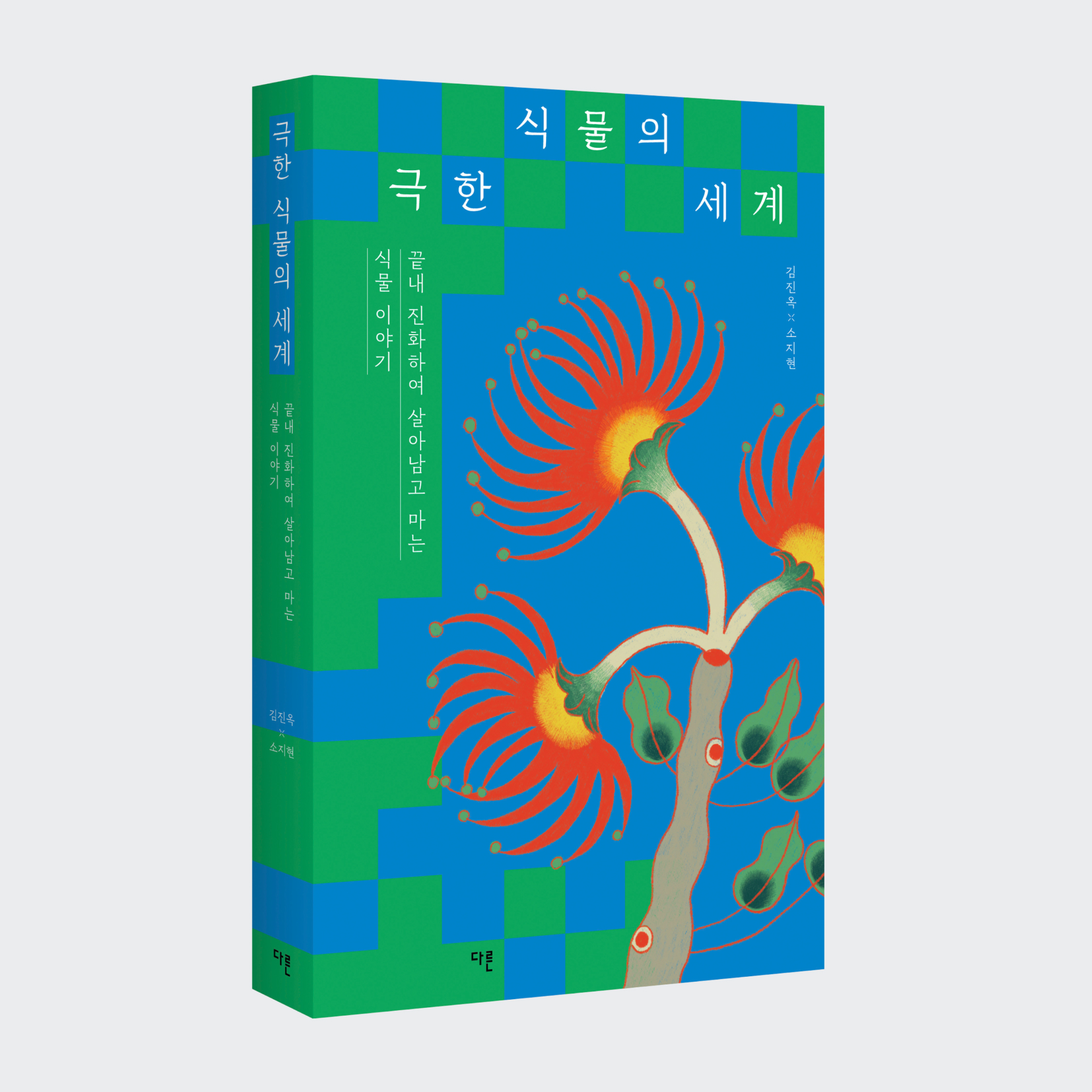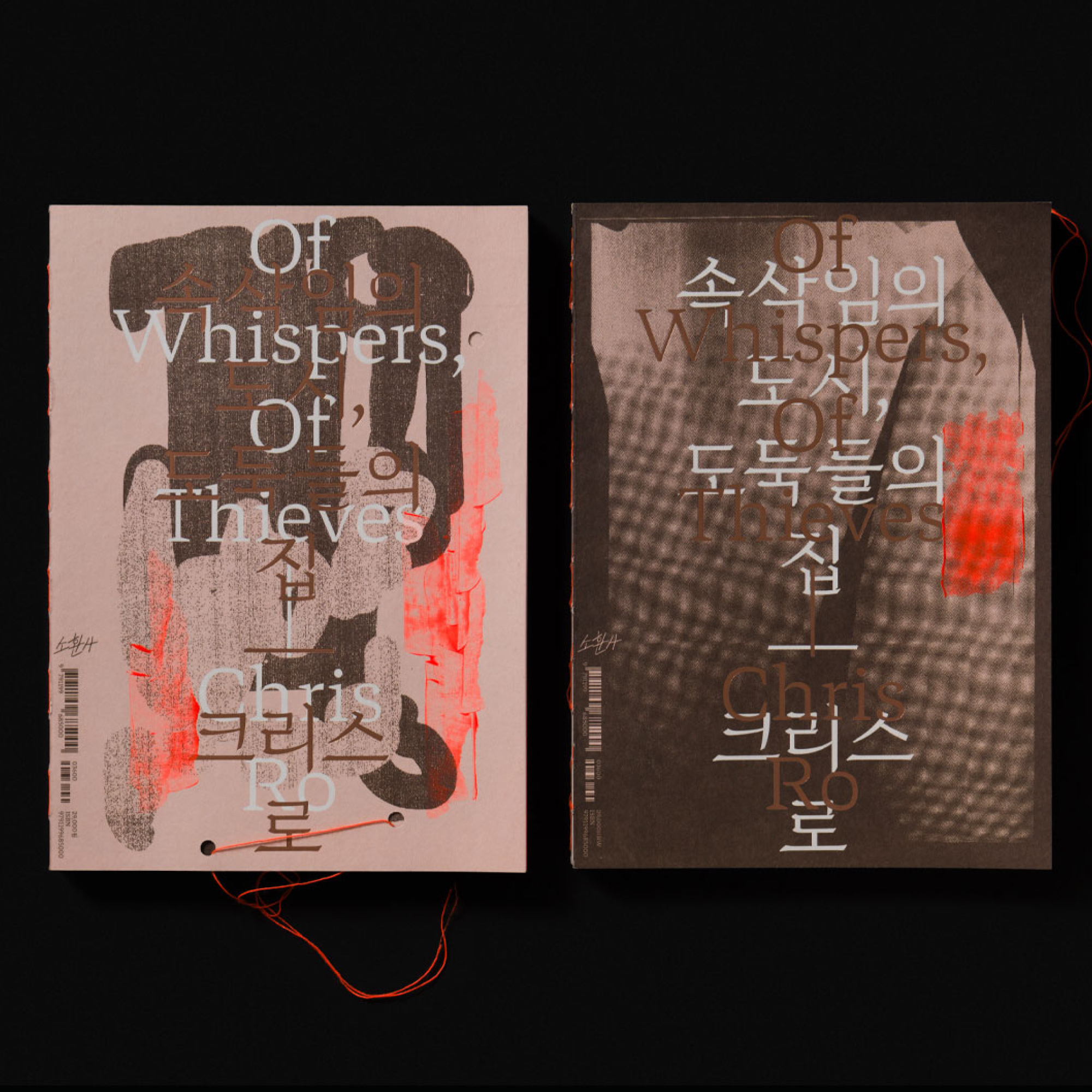
아르바나 패밀리
Arvana Family
‘아르바나’는 납작펜과 스카펠 나이프의 특성이 담긴, 날카로우면서도 부드러운 인상을 지닌 휴머니스트 스타일의 바이 스크립트 글꼴입니다. 아르바나는 한글 부리 글꼴 디자인을 붓이 아닌 서양의 쓰기 도구들로 써본 형태를 상상하면서 시작되었습니다. 필획의 섬세함을 유지하는 선에서 날카로운 형태를 부드럽게 나타내고자 했고, 디자이너의 손글씨 느낌을 일부 자소에 반영하였습니다. 예를 들어, 받침 니은과 리을에 있는 약간의 굴곡은 캘리그라픽 흘림의 형태를 차용함과 동시에 작업자의 이름에 들어간 자음을 강조하여 본문에 개성을 부여하고자 했습니다. 아르바나는 제 6회 방일영재단 글꼴창작지원공모에 선정되었습니다.